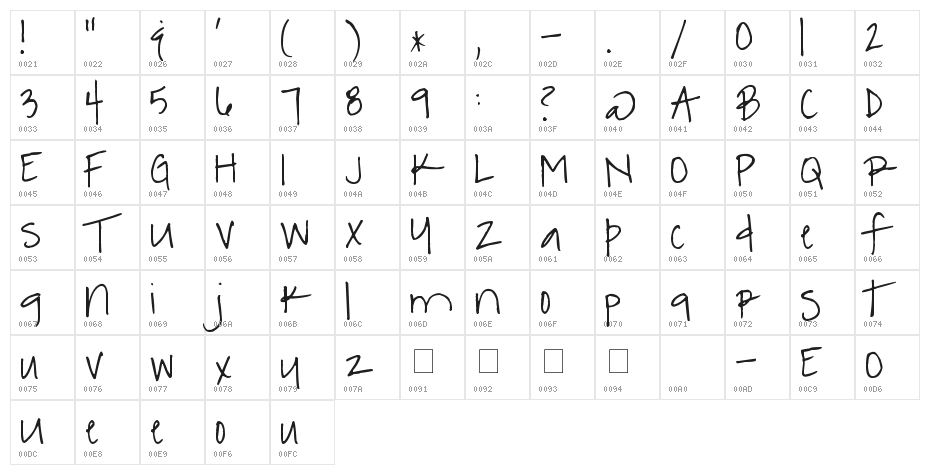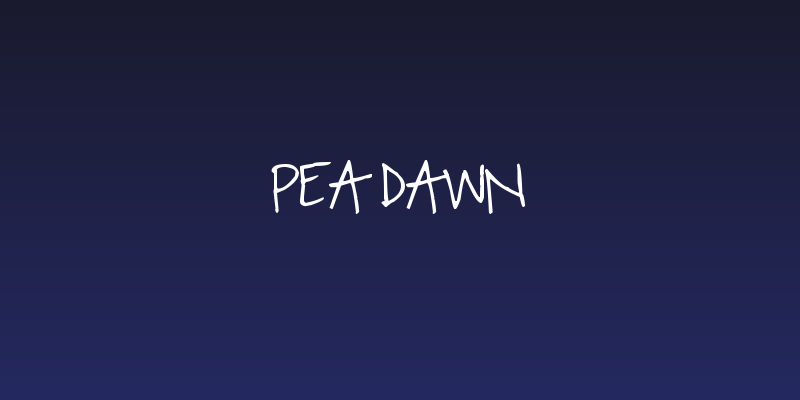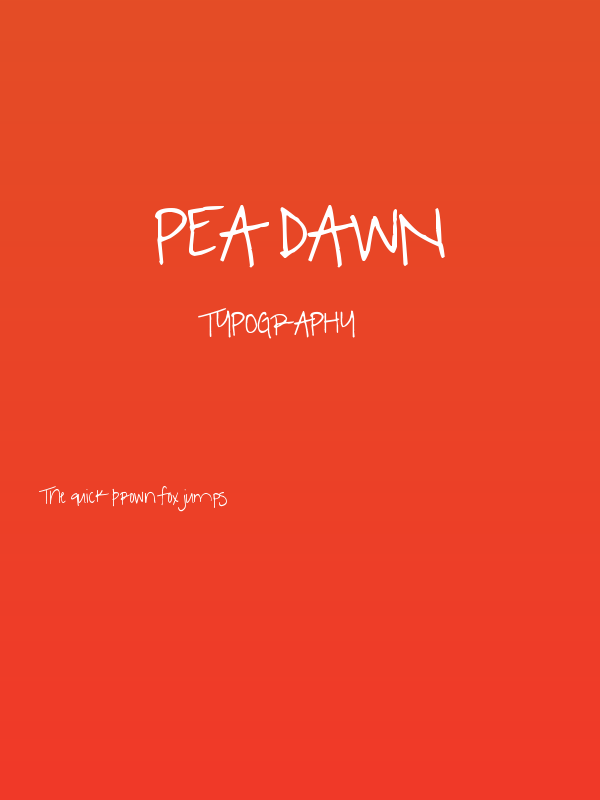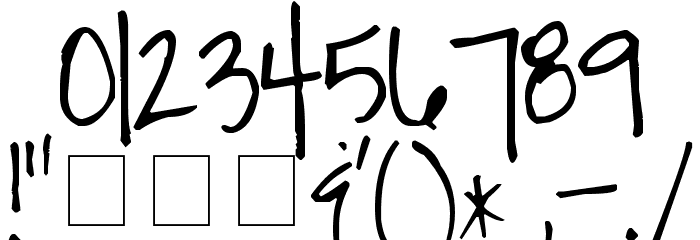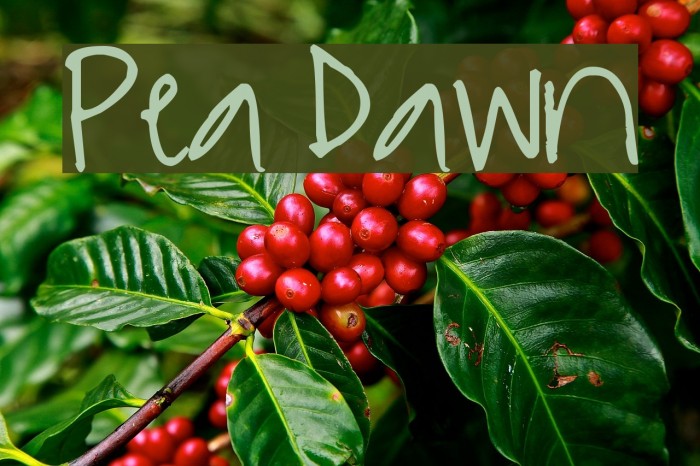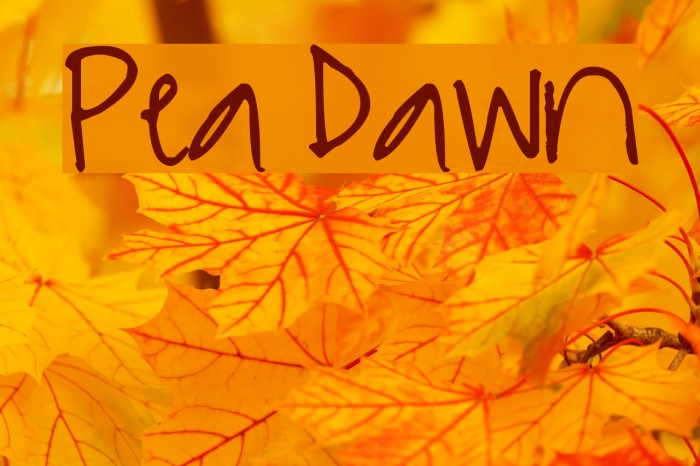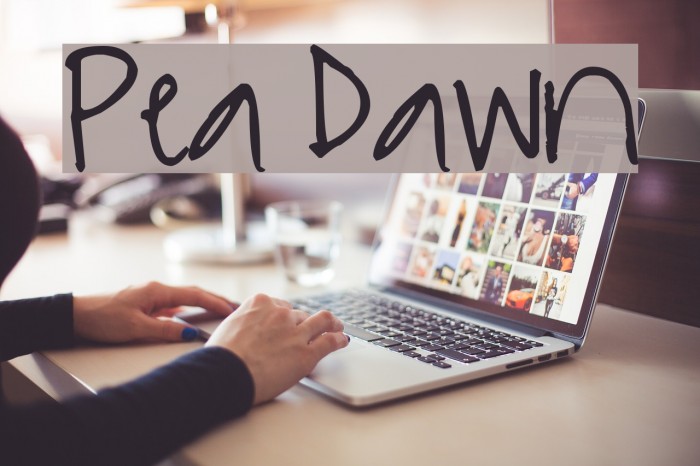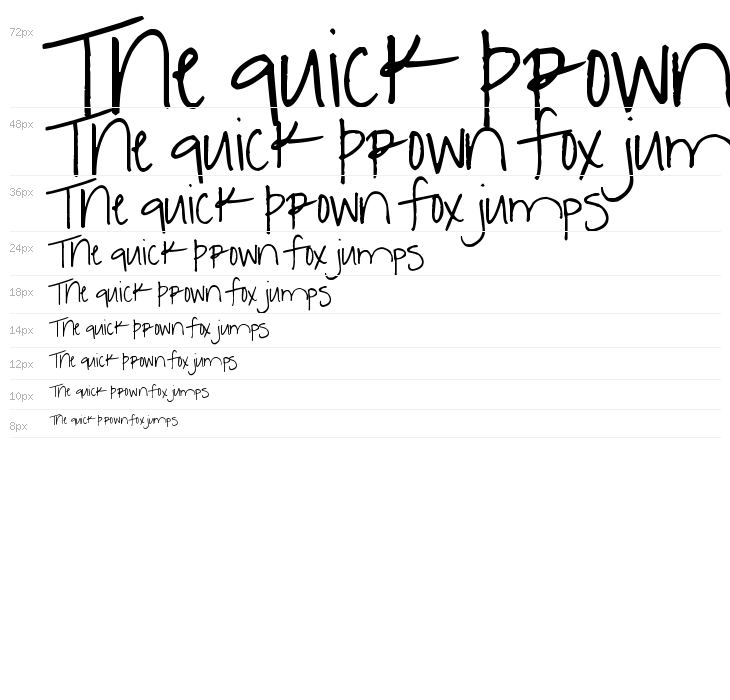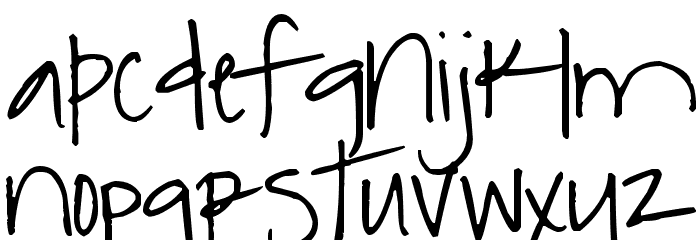
Pea Dawn Font
| Stile generale | Casual, Playful |
| Caso d'uso | Headlines, Informal text, Personal projects |
| Progetti proposti | Ideal for greeting cards, personal blogs, children's books, and informal branding. |